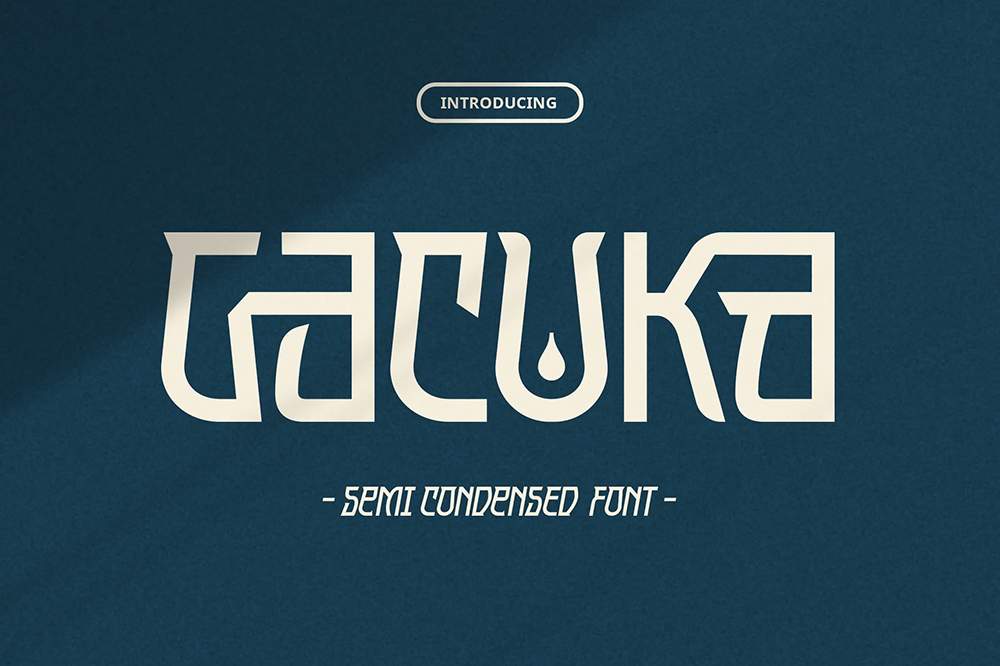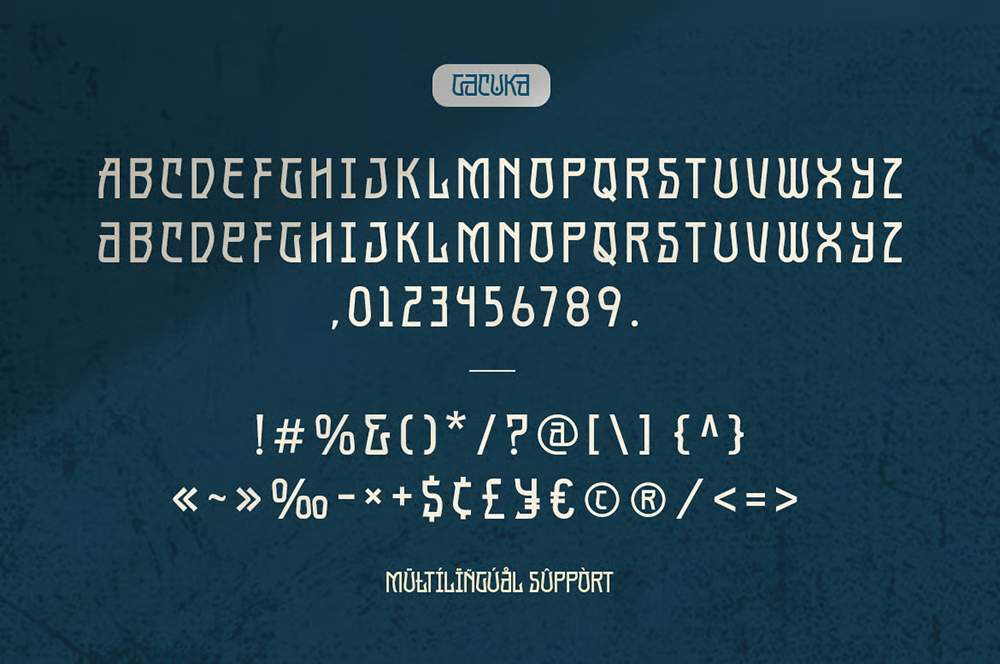
فونت پرمیوم و انگلیسی Gacuka Font یک فونت نیمهفشرده مدرن است که خلاقیت را با طراحی تمیز ترکیب میکند و آن را به انتخابی برجسته برای تیترهای…
فونت پرمیوم و انگلیسی Gacuka Font یک فونت نیمهفشرده مدرن است که خلاقیت را با طراحی تمیز ترکیب میکند و آن را به انتخابی برجسته برای تیترهای تأثیرگذار و عناوین خیرهکننده تبدیل میکند. Gacuka با فرم حروف منحصر به فرد و رسای خود، ضمن حفظ خوانایی و تعادل، شخصیتی متمایز ارائه میدهد و دارای منحنیهای نرم، لبههای تیز و ریتمی پویا است که آن را از فونتهای سنسسریف سنتی متمایز میکند. این فونت مجهز به لیگاتورهایی است که با دقت ساخته شدهاند و جریان بصری را افزایش میدهند و به متن ظاهری شخصیسازی شده و پیچیده میدهند که برای لوگوها و پوسترها ایدهآل است.
مزایای استفاده از فونت لاتین Gacuka چیست؟